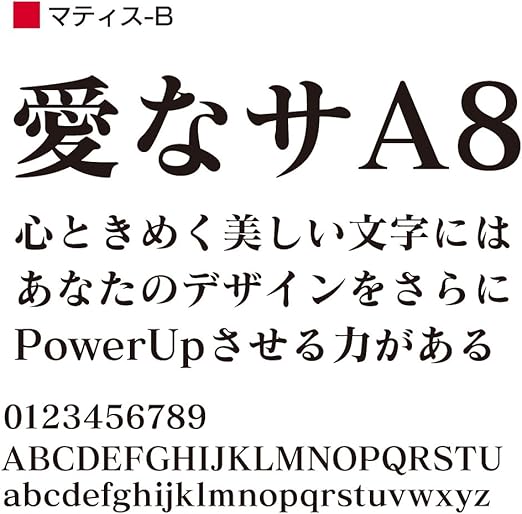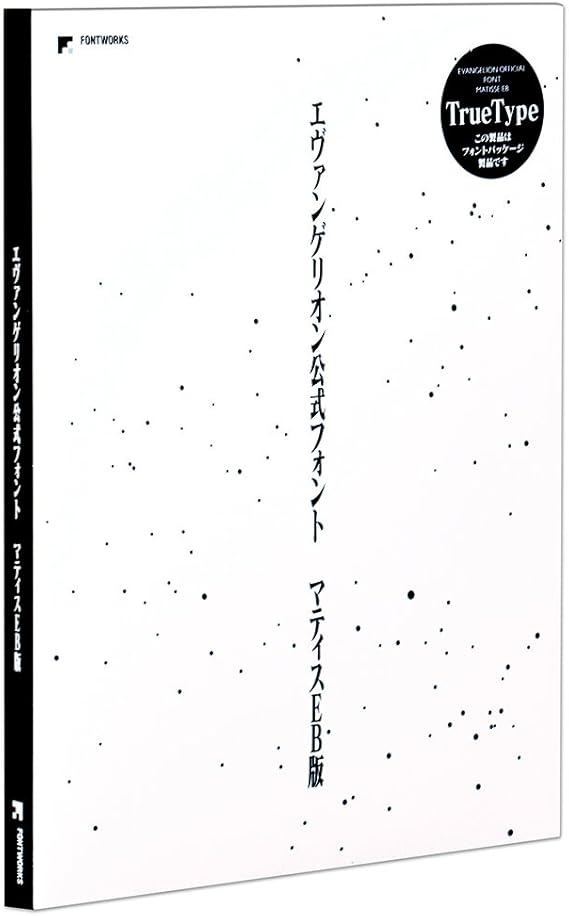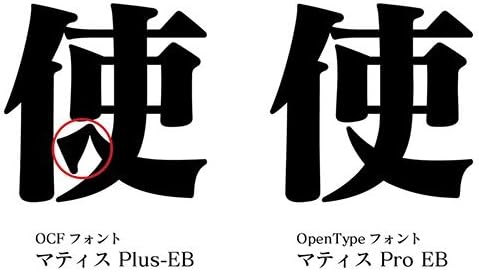
マティス フォント ダウンロード
フォントを見る マティス M ベーシックな部分を大切にしたデザインの中にも、古さを感じさせないシャープさと柔らかで優しい曲線の表情を合わせ持った明朝体です。. フォントワークス OpenTypeフォント クラシックシリーズ ダウンロード版 Mac用 OpenTypeフォント/書体名: 明朝体「マティス ProUB for Mac」/仕様: Adobe Japan14 Pro仕様. 以下のページからフォントをダウンロードしてインストールしてください。 CLIP STUDIO PAINT EX/PRO限定特典 追加素材のダウンロード ※zip圧縮されたファイルとなっているため、zip解凍してご利用ください。※利用期限があるライセンスにはフォントは付属しません。.
フォントを見る マティス M ベーシックな部分を大切にしたデザインの中にも、古さを感じさせないシャープさと柔らかで優しい曲線の表情を合わせ持った明朝体です。. まきばフォント太P v13 → ダウンロードはこちらから <説明> ・やっぱり可愛いフォントもほしくなって作ってみた手書きフォント。 ・TrueTypeフォント。WinXPまで/MacOS X以降で使えます。 ・日本語2バイトかな文字フォント。等幅。一応縦書き対応。. フォントワークスコレクションの中からクラシックシリーズ29書体の ダウンロード版Windows用OpenTypeフォント。 書体名:明朝体《マティス ProL》 仕様:Adobe Japan14 Pro仕様(15,444文字収録).
このフォントはエヴァ公式フォントとして発売されています。 Amazon フォントワークス エヴァンゲリオン公式フォント マティスEB Truetype版 楽天 エヴァンゲリオン公式フォント マティスEB Truetype版() しかし、購入すると、そこそこのお値段します。. フォントを見る マティス M ベーシックな部分を大切にしたデザインの中にも、古さを感じさせないシャープさと柔らかで優しい曲線の表情を合わせ持った明朝体です。. 「マティス Pro」で「太字」にチェックを入れると使用できますよ。 使い方 「CloudAlpaca」を起動するとクラウドサービスのウィンドウが表示。 ここでログインをしないとフォントワークスのフォントは使えません。 テキストの入力画面はこんな感じ。.
『エヴァンゲリオン公式フォント マティスEB TrueType 版』が11月10日にフォントワークスより発売開始! 「新世紀エヴァンゲリオン」で印象的なあの書体“エヴァ明朝”が、PC フォントとして利用可能に!. フォントワークス OpenTypeフォント クラシックシリーズ ダウンロード版 Mac用 OpenTypeフォント/書体名: 明朝体「マティス ProUB for Mac」/仕様: Adobe Japan14 Pro仕様. フォントだから大きさも字の濃さも自由。背景に色をつければ白抜き文字も 楽チン! ダウンロード マニュアル なぞりがきフォント version up 履歴 05/8/7 v0 全角半角数字を追加。.
フォントワークスコレクションの中からクラシックシリーズ(全29書体)のダウンロード版 Windows用 OpenTypeフォント(単体製品)です。 収録書体名 明朝体「マティス ProDB」 仕様 Adobe Japan 14 Pro仕様(文字収録) 書体の特長. このフォントはエヴァ公式フォントとして発売されています。 Amazon フォントワークス エヴァンゲリオン公式フォント マティスEB Truetype版 楽天 エヴァンゲリオン公式フォント マティスEB Truetype版() しかし、購入すると、そこそこのお値段します。. エヴァフォント「マティスProEB」には無料ダウンロードはありません。 フリーフォントでも「極太明朝体」はありません。 エヴァファンなら「マティスProEB Truetype版」がベスト。 有料フォントを格安で購入するなら「AR 明朝体U」がおすすめ。.
インターネット上でかわいいフォントを見かけました。無料だったのでダウンロードしてみましたが、 実際に使用するにはどうしたらいいですか? a 「フォント」をインストールし、利用可能なソフトに適用しましょう. フォントワークスコレクションの中からクラシックシリーズ(全29書体)のダウンロード版 Windows用 OpenTypeフォント(単体製品)です。 収録書体名 明朝体「マティス ProDB」 仕様 Adobe Japan 14 Pro仕様(文字収録) 書体の特長. エヴァンゲリオン公式フォント マティスEB TrueType版 数量限定!在庫限り!お早めにお買い求めください! 「新世紀エヴァンゲリオン」において「時に、西暦15年」「使徒、襲来」など、黒字に白抜きの文字表現で大反響を呼び、ファンの間では“エヴァ明朝”とも呼ばれる「マティスEB」が.